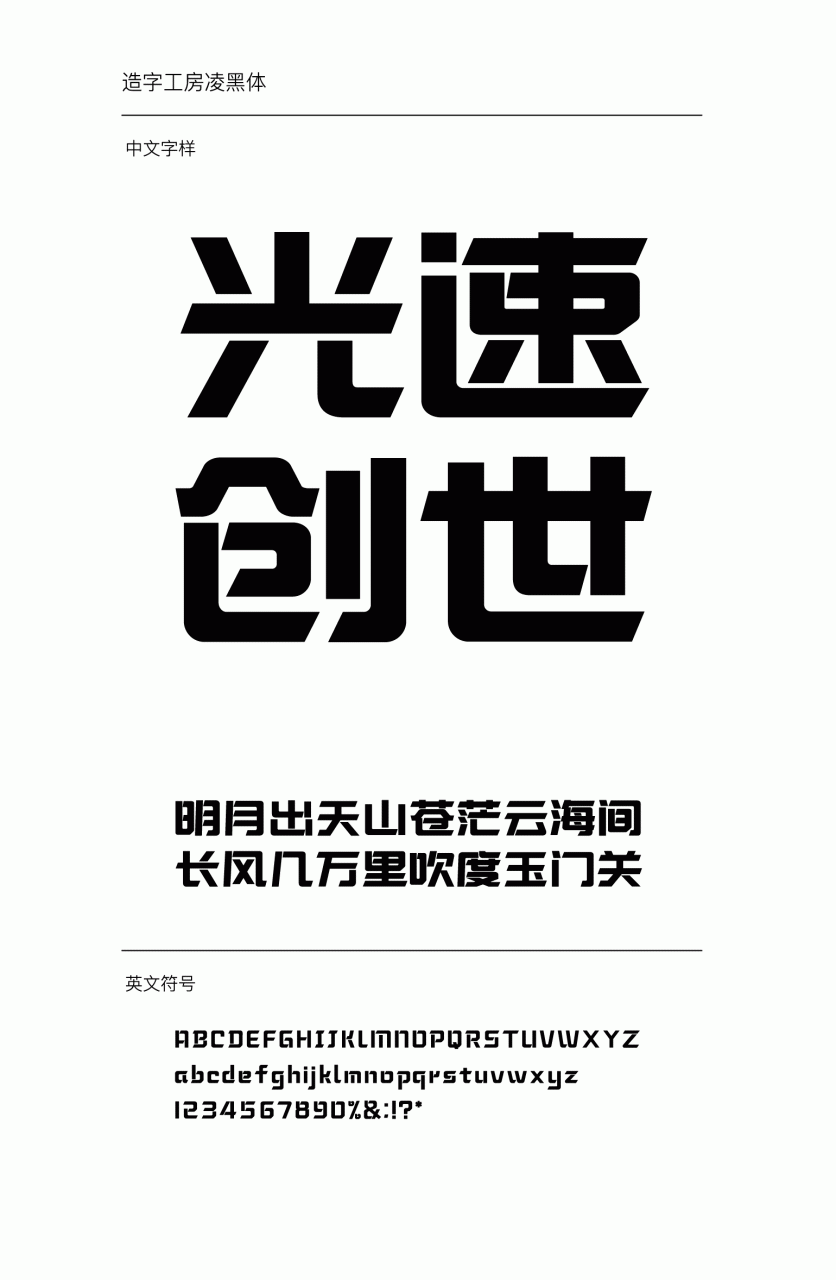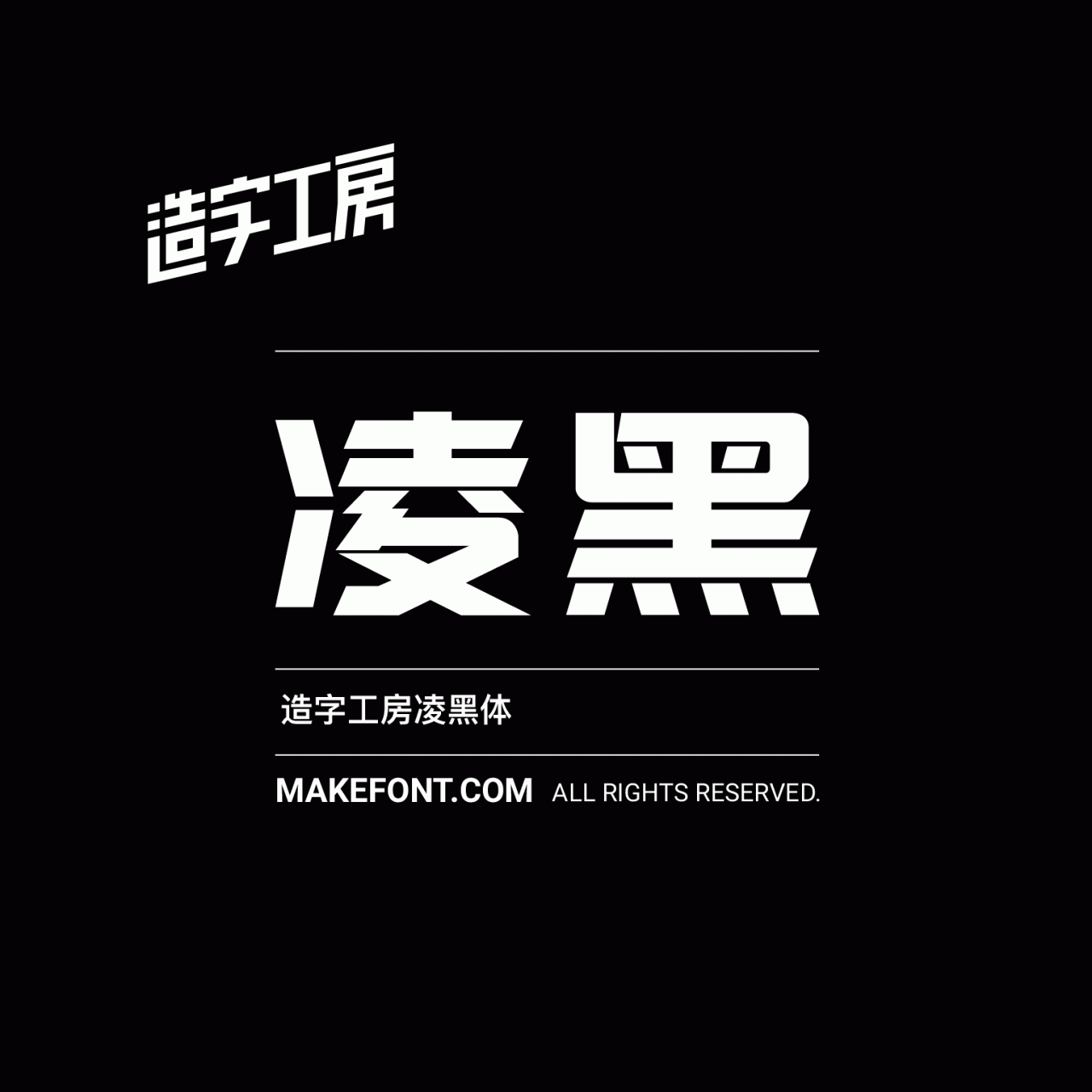
造字工房凌黑常规体设计说明
造字工房凌黑体字形饱满、整体风格粗旷厚重,字重浑厚、棱角分明,结构方正沉稳不失时代气息,横的切角处理让字体更显刚毅。笔画与笔画间的断层处理,使其笔画顿挫有力、峻拔刚断、有抑扬顿挫之感。给整体字形带来很强的现代科技感。此款字体适用于科技竞技环境中,具有较大范围的应用空间。 本字体为简体字库,采用OpenType/CID格式,Adobe-GB1-5编码。基于中华人民共和国GB2312-80字符集标准,另按需添加101个汉字。共收容字数6864CJK汉字,ASCII常用字符100个。